Las 15 mejores fuentes de lucha libre de 2023 (gratuitas y premium)
Publicado: 2023-08-21¿Es usted un diseñador gráfico que busca la fuente perfecta para mejorar sus proyectos con temas de lucha libre? ¡No busque más! En esta publicación de blog, hemos compilado una lista de las 15 mejores fuentes de lucha libre solo para ti.
Pero quizás te preguntes por qué estas fuentes son las mejores. ¿O cómo pueden mejorar mis diseños? No se preocupe, lo tenemos cubierto.
En este artículo, no solo mostraremos algunas increíbles fuentes de lucha libre, sino que también te brindaremos estadísticas y datos interesantes sobre cada fuente.
Creemos que comprender los antecedentes y las características únicas de estas fuentes puede ayudarlo a tomar una decisión informada al seleccionar la perfecta para su proyecto.
Entonces, si estás listo para llevar tus diseños de lucha libre al siguiente nivel, ¡sigue leyendo! Nos sumergiremos en los detalles de las 15 mejores fuentes de lucha libre, brindándole una muestra de sus estilos, inspiraciones y por qué son imprescindibles para cualquier diseñador gráfico en la industria de la lucha libre.
¡Comencemos y exploremos juntos el apasionante mundo de las fuentes de lucha libre!
Las mejores fuentes premium de lucha libre
¿Buscas agregar algún impacto visual a tus diseños de lucha libre? ¡No busques más que nuestra lista seleccionada de las 15 mejores fuentes de lucha libre! En esta sección, destacamos lo mejor de lo mejor con nuestra selección de fuentes de lucha libre premium que seguramente llevarán tus proyectos al siguiente nivel.
¡Mira estas fuentes de primer nivel y prepárate para hacer una declaración en tus diseños!
Kabadí
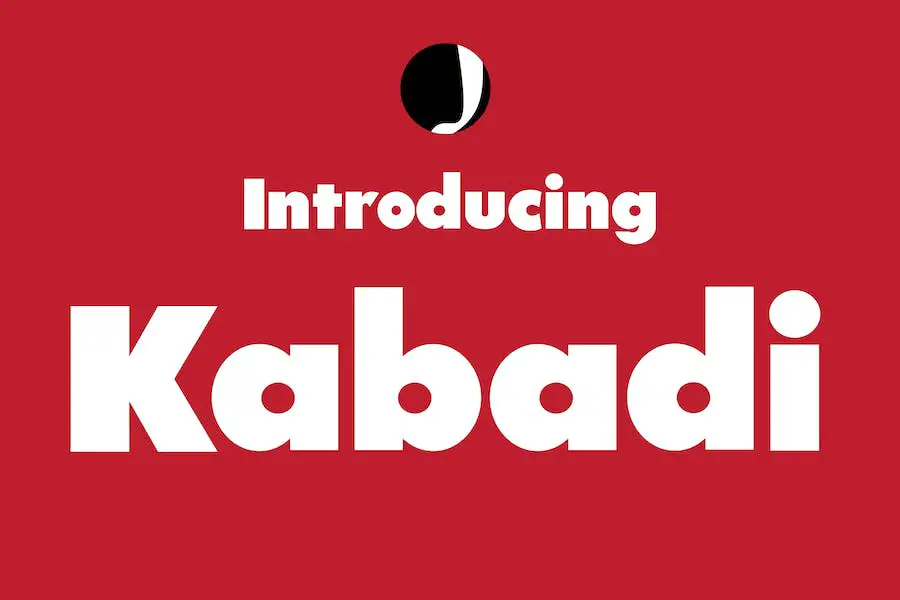
Kabadi es una fuente de visualización en negrita perfecta para diseñadores gráficos que buscan agregar un toque de singularidad a sus proyectos. Con su nombre derivado de la palabra punjabi que significa lucha libre, esta fuente rinde homenaje a la naturaleza vibrante y enérgica del deporte.
Ideal para titulares, diseños de revistas y portadas, Kabadi aporta un elemento poderoso e impactante a cualquier diseño. Sus letras atrevidas y llamativas hacen una declaración y captan la atención de los espectadores.
Ya sea que estés trabajando en un cartel para un evento de lucha libre o diseñando productos para un fanático de la lucha libre, Kabadi agregará ese toque extra a tus creaciones. Sus personajes fuertes y distintivos crean una sensación de emoción e intensidad.
La naturaleza versátil de Kabadi significa que se puede utilizar para varios proyectos, lo que le brinda la flexibilidad de crear diseños impresionantes en diferentes medios. Ya sea que estés usando Canva o Cricut, esta fuente mejorará la apariencia de tu trabajo, haciéndolo destacar entre la multitud.
luchador
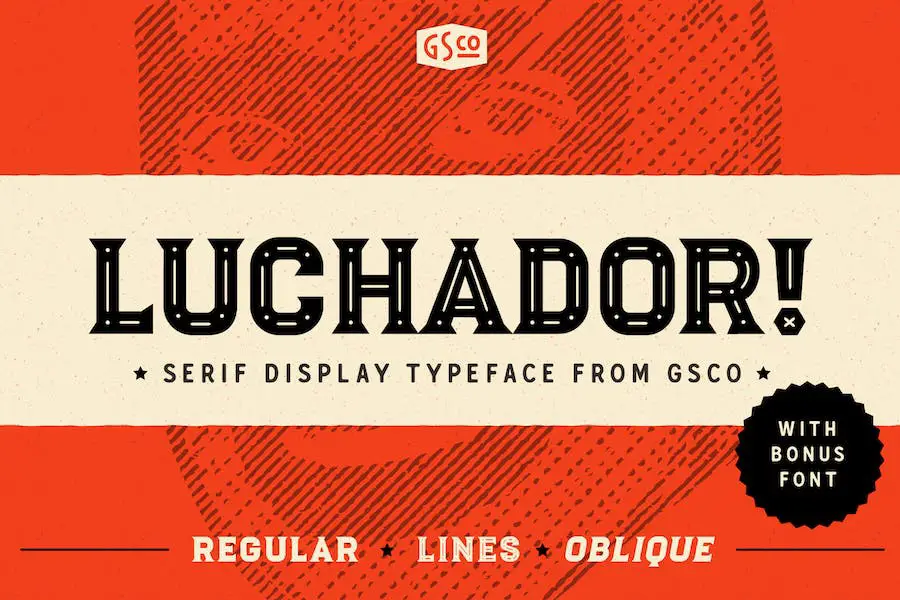
Luchador es un poderoso tipo de letra serif que viene en dos estilos. Con sus adornos en capas, agrega peso, carácter y carisma a cualquier proyecto, como un luchador mexicano.
Ya sea que estés diseñando para impresión o digital, Luchador es la elección perfecta para los diseñadores gráficos que desean llevar sus proyectos al siguiente nivel.
Esta fuente única es perfecta para crear diseños llamativos que se destacan en plataformas de redes sociales como Instagram. Si buscas agregar un toque de audacia y emoción a tus proyectos relacionados con la lucha libre, Luchador es imprescindible.
Los adornos en capas de Luchador te dan la libertad de personalizar tus diseños y agregar profundidad y dimensión. Con sus letras fuertes y atrevidas, Luchador hace una declaración y llama la atención al instante. Es el tipo de fuente que hará que tus diseños destaquen de la página.
Tatuajes de estruendo
¿Buscas una fuente que lleve tus proyectos con temas de lucha libre al siguiente nivel? No busques más que Rumble Tatuajes. Este increíble tipo de letra script, también conocido como It Typeface, está diseñado específicamente para agregar un toque atrevido y cautivador a sus diseños.
Con Rumble Tattoos, puedes crear logotipos impactantes que realmente representen el espíritu de la lucha libre. Sus trazos atrevidos y dinámicos le dan a sus logotipos una presencia poderosa, haciéndolos destacar entre la multitud.
Ya sea que estés diseñando para un evento de lucha libre o un equipo deportivo, esta fuente definitivamente dejará una impresión duradera.
No solo se limita a logotipos, Rumble Tattoos también es perfecto para diseños de carteles. Sus formas de letras únicas y sus detalles intrincados añaden una sensación de dramatismo e intensidad a cualquier cartel.
Ya sea que estés promocionando un combate de lucha libre o creando obras de arte para un evento con temática de lucha libre, esta fuente seguramente llamará la atención de tu audiencia.
MAHIRA
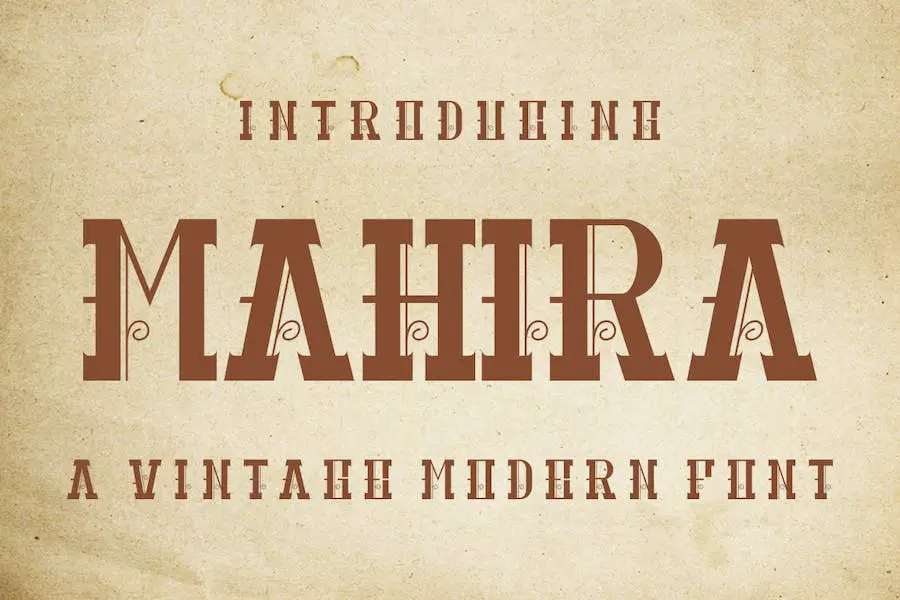
MAHIRA es una fuente de visualización vintage perfecta para diseñadores gráficos que desean mejorar el diseño de sus proyectos. Con sus usos versátiles, esta fuente es una gran adición al conjunto de herramientas de cualquier diseñador.
Con su encanto retro y estilo único, MAHIRA añade un toque de nostalgia a cualquier proyecto de diseño. Sus letras atrevidas y su aspecto icónico ayudan a captar la atención y crear una impresión memorable.
Ya sea que estés trabajando en un logotipo para una cafetería de inspiración vintage o diseñando un cartel para un evento con temática retro, esta fuente agregará el toque perfecto de estilo vintage.
Una de las características más destacadas de MAHIRA es su versatilidad. Se puede utilizar para una amplia gama de proyectos de diseño, lo que la convierte en la fuente preferida de muchos diseñadores gráficos.
La flexibilidad de la fuente permite una integración perfecta en varios estilos y temas de diseño, lo que garantiza que sus proyectos se destaquen entre la multitud.
Merauq
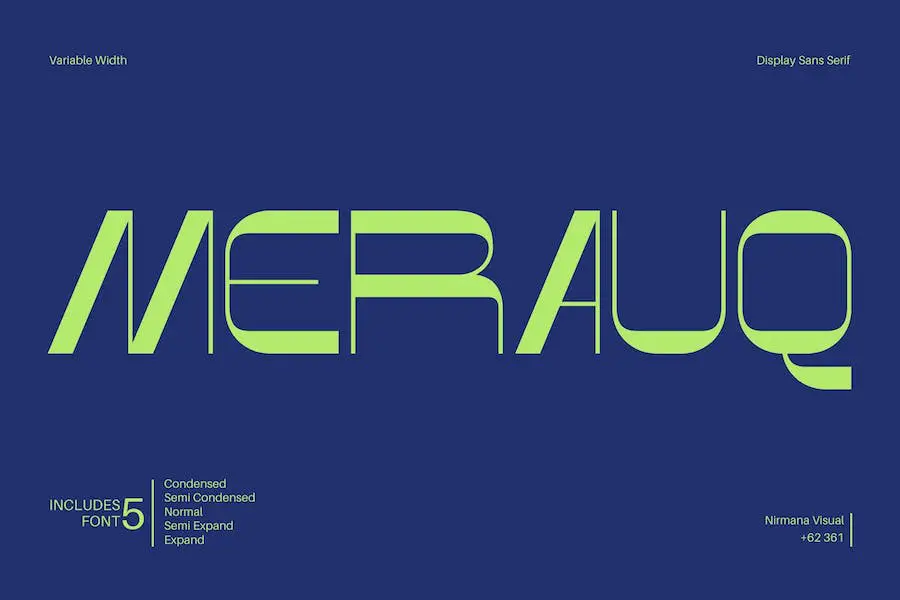
Merauq es una fuente que proporciona una hermosa armonía tipográfica para diversos proyectos de diseño. Con sus 5 anchos, es perfecto para crear logotipos y materiales de marca, publicaciones en redes sociales, anuncios y diseños de productos.
Esta fuente es una herramienta versátil que los diseñadores gráficos pueden utilizar para mejorar el atractivo visual de sus proyectos. Sus 5 anchos permiten flexibilidad y personalización, asegurando que pueda adaptarse a las necesidades específicas de diferentes elementos de diseño.
Ya sea que esté trabajando en el logotipo de una empresa o creando publicaciones llamativas en las redes sociales, Merauq lo tiene cubierto. Su aspecto elegante y armonioso añade un toque de profesionalismo y sofisticación a cualquier diseño.
Los atributos de la fuente la convierten en una excelente opción para los diseñadores que desean mejorar la estética general de sus proyectos. Desde su apariencia limpia y moderna hasta su amplia gama de anchos, esta fuente ofrece infinitas posibilidades para crear diseños visualmente impresionantes.
Cista Simoly
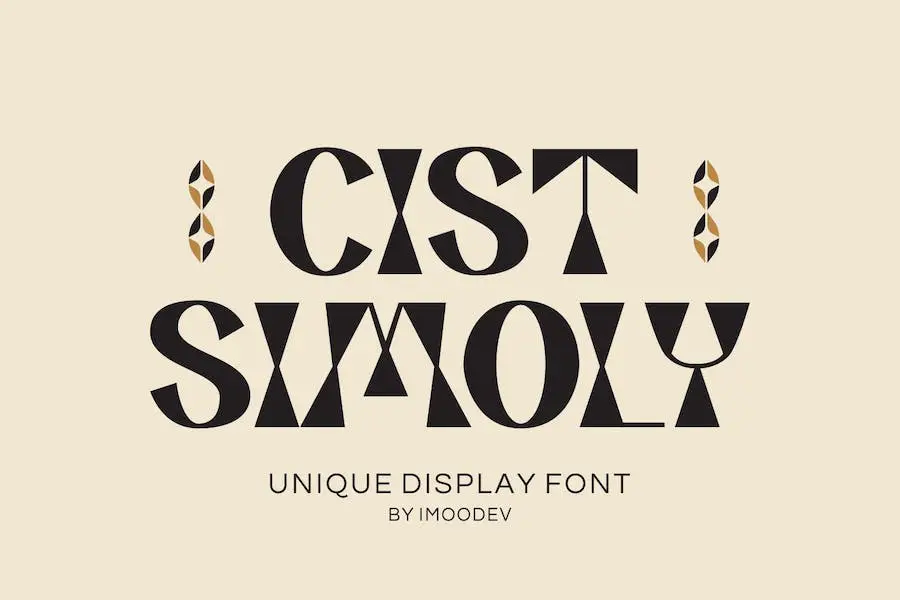
Cist Simoly es una fuente clásica moderna que irradia elegancia visual con sus suaves curvas y hermosas ligaduras. Esta fuente añade un toque de sofisticación a cualquier diseño, haciendo que tu trabajo luzca real y atractivo.
Ya sea que estés creando un logotipo, un póster o un sitio web, Cist Simoly es la fuente perfecta para mejorar el diseño general.
Con su estilo claro y legible, Cist Simoly garantiza que su texto sea fácilmente legible, incluso en tamaños pequeños. Las suaves curvas de las letras le dan a esta fuente un aspecto contemporáneo y elegante, mientras que las ligaduras añaden un nivel extra de refinamiento.
Esta fuente realmente se destaca entre la multitud, permitiéndote hacer una declaración con tu diseño.
Lo que distingue a Cist Simoly es su capacidad para combinar a la perfección elementos clásicos y modernos. Combina el atractivo atemporal de una fuente clásica con las líneas limpias y la sensación contemporánea de una fuente moderna.
Esta combinación única le da a su diseño una sensación de equilibrio y armonía, haciéndolo visualmente atractivo y agradable a la vista.
aturdimiento
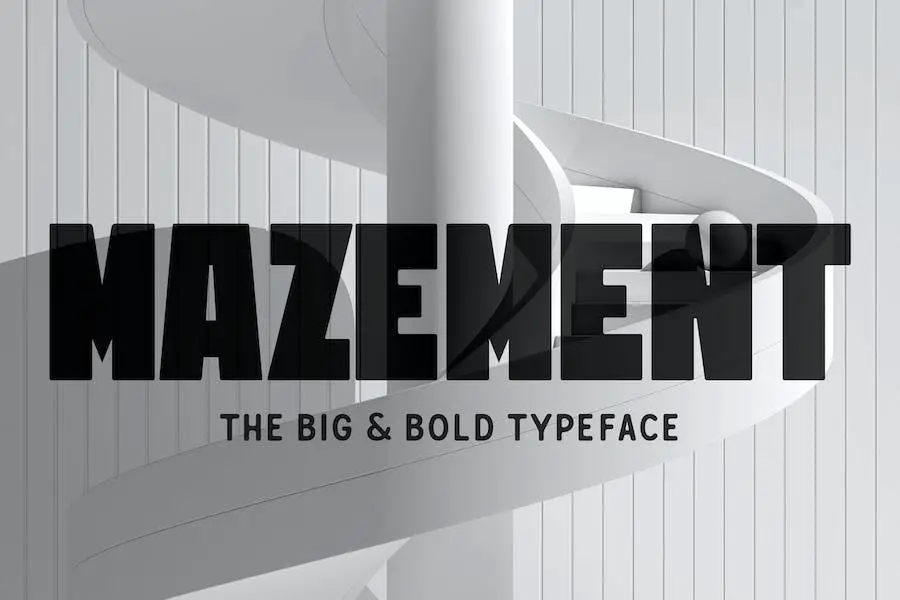
Mazement es un tipo de letra poderoso e impactante que ofrece más de 300 glifos y admite múltiples idiomas latinos. Con su diseño atrevido y macizo, pretende llamar la atención y dominar el espacio que ocupa. Perfecta para visualización y titulares, esta fuente sigue el lema "Cuanto más grande, mejor".
Con Mazement, tendrás acceso a una amplia gama de personajes y símbolos, lo que te permitirá crear diseños llamativos que se destacan. Su gran peso y sus líneas atrevidas lo hacen ideal para llamar la atención y llamar la atención.
Ya sea que esté trabajando en un póster, un logotipo o cualquier otro proyecto de diseño que requiera una fuente llamativa y llamativa, Mazement lo tiene cubierto. Su apariencia espectacular garantiza que su mensaje se transmita alto y claro.
Darkville
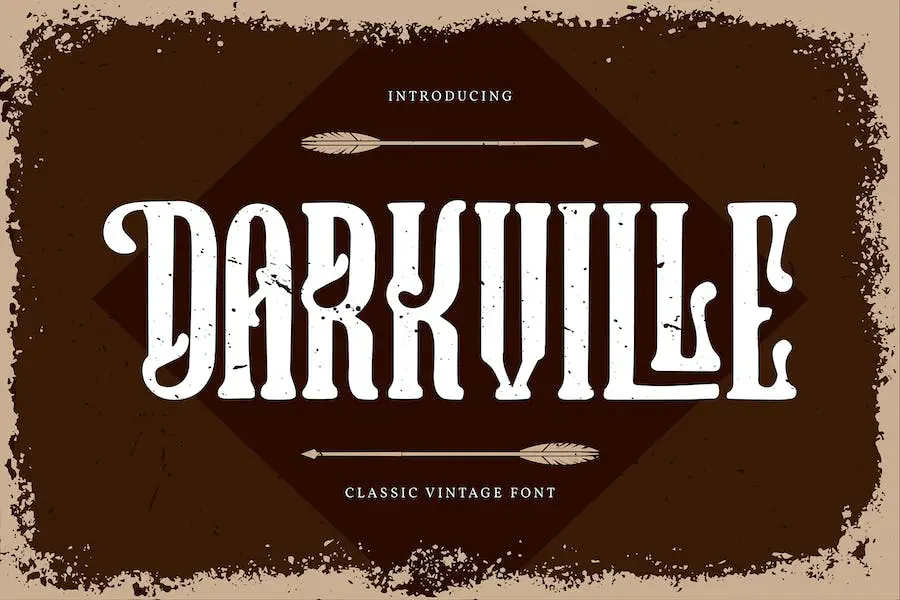
Darkville es una fuente clásica vintage con estilo caligráfico. Agrega un toque de belleza y elegancia a diversos proyectos de diseño, como tarjetas de invitación, tarjetas de felicitación, materiales de marca, tarjetas de presentación, citas y carteles.
Con su aspecto único y atemporal, Darkville es perfecto para añadir un toque vintage y nostálgico a tus diseños. Ya sea que estés trabajando en un proyecto para una boda, un evento especial o simplemente quieras darle a tus diseños un toque clásico, Darkville es una fuente imprescindible para los diseñadores gráficos.
Su versatilidad y atractivo artístico lo convierten en una excelente opción para cualquier proyecto de diseño. Dale a tus diseños un toque de elegancia con Darkville.
Goldrick
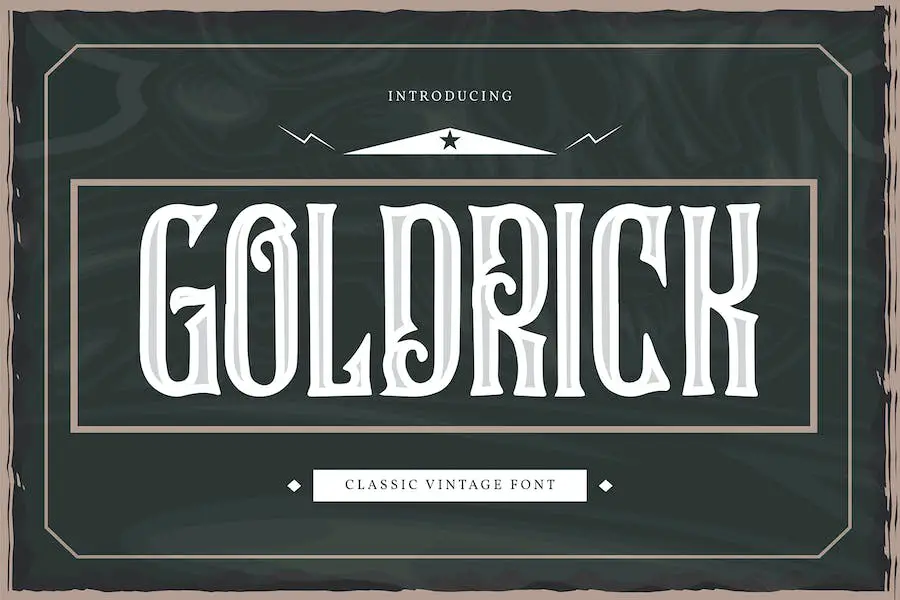
Goldrick es una fuente clásica vintage que cuenta con un hermoso estilo de caligrafía. Es perfecto para mejorar el diseño de diversos proyectos como invitaciones, tarjetas de felicitación, materiales de marca, tarjetas de presentación, citas, carteles y más.
Con su aspecto elegante y con estilo, Goldrick añade un toque de sofisticación a cualquier diseño. Su estilo de caligrafía brinda una sensación clásica y atemporal, lo que la convierte en una fuente ideal para los diseñadores gráficos que buscan mejorar sus proyectos.
Ya sea que esté creando invitaciones de boda o materiales promocionales, Goldrick seguramente impresionará con su estética ornamentada y cautivadora.
Samuel Wickley
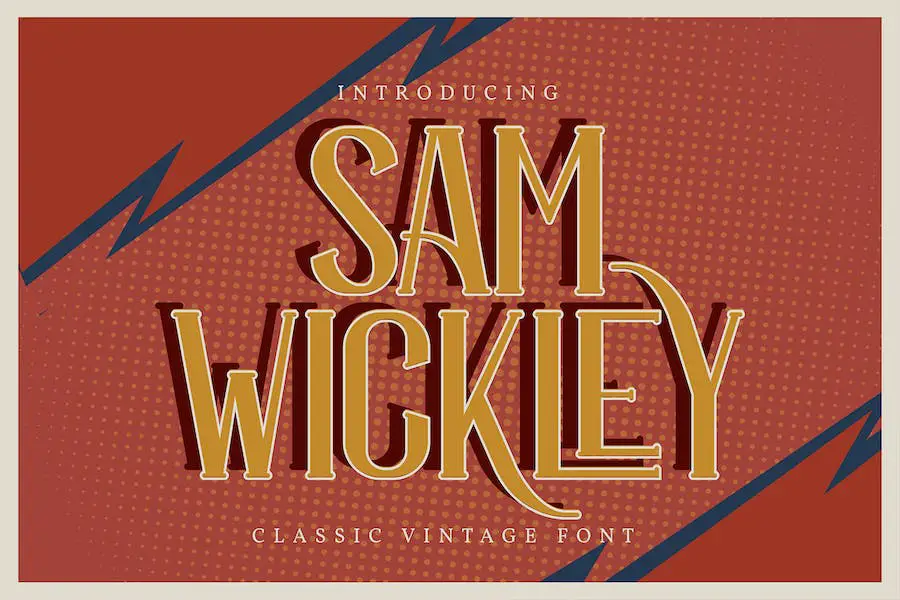
Sam Wickley es una fuente clásica vintage que añade un toque de elegancia y encanto a cualquier proyecto de diseño. Con su estilo de caligrafía, esta fuente es perfecta para crear impresionantes invitaciones, tarjetas de felicitación, materiales de marca, tarjetas de presentación, citas, carteles y más.
Las exquisitas curvas y los intrincados detalles de Sam Wickley lo convierten en una opción destacada para los diseñadores gráficos que buscan mejorar sus proyectos.
Ya sea que esté trabajando en una invitación de boda o en un póster promocional, esta fuente mejorará sin esfuerzo el diseño general y creará una impresión duradera.
Una de las características más destacadas de Sam Wickley es su atractivo atemporal. Con su estética vintage, aporta una sensación de nostalgia y sofisticación a cualquier obra. Capta sin esfuerzo la esencia del diseño clásico y al mismo tiempo mantiene un toque contemporáneo.
Las mejores fuentes de lucha libre gratuitas
¿Buscas agregar una tipografía feroz e impactante a tu próximo proyecto de diseño? ¡No busque más! En esta sección, hemos seleccionado las mejores fuentes de lucha libre gratuitas que seguramente elevarán tus diseños a un nivel de campeonato.
Así que ponte las botas y sumérgete en esta colección: ¡no querrás perderte estas fuentes impresionantes!
Lucha grecorromana lubricada
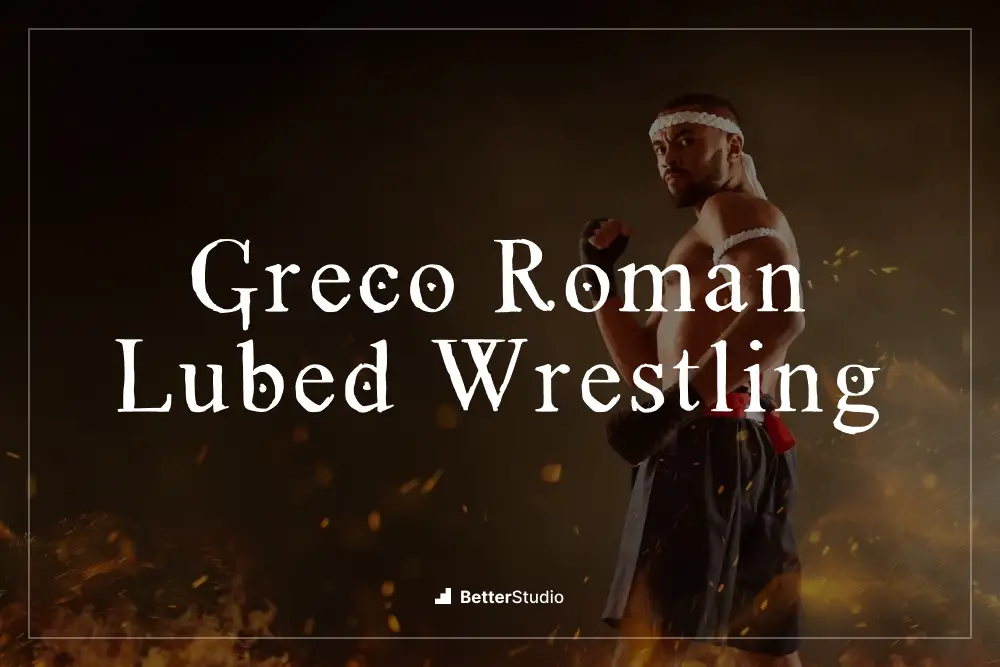
Greco Roman Lubed Wrestling es una fuente diseñada específicamente para diseñadores gráficos que buscan elevar el diseño de sus proyectos. Con su estilo único y líneas elegantes, añade un toque de sofisticación a cualquier diseño.
Esta fuente es perfecta para crear títulos, logotipos o cualquier otro elemento creativo cautivadores que requiera un impacto visual poderoso y dinámico.
Greco Roman Lubed Wrestling combina la elegancia de la tipografía romana tradicional con un toque moderno. Su aspecto elegante y atrevido lo hace ideal para diseños relacionados con los deportes, especialmente aquellos relacionados con la lucha libre.
La curvatura única de la fuente y sus bordes afilados le dan una sensación fuerte y enérgica, capturando perfectamente el espíritu del deporte y añadiendo una sensación de poder e intensidad a sus diseños.
LOGOTIPO DE TNA
TNA Logo es una fuente fantástica que es perfecta para diseñadores gráficos que buscan mejorar sus proyectos. Esta fuente aporta un aire fuerte y audaz a cualquier diseño, lo que la hace ideal para proyectos con temática de lucha libre. Creado por 24hourfonts, agrega un toque único y poderoso a tu trabajo.
La fuente del logotipo TNA tiene un estilo distintivo que captura la esencia de la lucha libre. Sus bordes afilados y líneas fuertes le dan un aspecto resistente e impactante.
Ya sea que estés creando materiales promocionales para un evento de lucha libre o diseñando productos para un fanático de la lucha libre, esta fuente definitivamente hará una declaración.
Una de las características destacadas de TNA Logo es su versatilidad. Funciona bien con varios elementos de diseño, incluidos carteles, logotipos, camisetas y más. Su diseño atrevido y llamativo capta la atención del espectador y deja una impresión duradera.
Con esta fuente, tus proyectos tendrán ese aspecto profesional y pulido que los hará destacar entre la multitud.
Evolucionado
Evolved, creada por JK Typeface, es una fuente fantástica que es perfecta para diseñadores gráficos que buscan mejorar los diseños de sus proyectos.
Esta fuente cuenta con un estilo único y moderno que seguramente llamará la atención. Tiene una apariencia elegante y profesional que puede agregar un toque de elegancia a cualquier diseño.
Evolved viene con una amplia gama de opciones, incluidos diferentes pesos y estilos, lo que permite a los diseñadores elegir la opción perfecta para su proyecto. Ya sea que estés buscando una fuente atrevida y que llame la atención o una más sutil y sofisticada, Evolved tiene lo que necesitas.
Una de las características más destacadas de Evolved es su versatilidad. Se puede utilizar en varios diseños, desde carteles y logotipos hasta sitios web y gráficos de redes sociales. Cualquiera que sea su proyecto, esta fuente puede mejorar su apariencia general.
Pelearse
Brawl, de Baja La Luna Producciones, es una fuente que todo diseñador gráfico debería considerar agregar a su colección. Con su diseño atrevido y poderoso, Brawl es perfecto para crear diseños llamativos e impactantes para cualquier proyecto con temática de lucha libre.
Uno de los atributos destacados de Brawl es su versatilidad. Ya sea que estés diseñando un cartel, un logotipo o un producto para un evento de lucha libre, esta fuente puede aportar ese toque e intensidad extra a tu trabajo.
Grita acción y emoción, lo que lo convierte en la opción ideal para capturar la esencia del mundo de la lucha libre.
Las líneas fuertes y nítidas de la fuente le dan una sensación moderna y atrevida, agregando un toque contemporáneo a sus diseños. Su naturaleza audaz garantiza que su texto se destaque y sea fácilmente legible, incluso desde la distancia. Brawl llama la atención y exige ser notado.
Caída retumbante
Rumble Tumble, creada por Iconian Fonts, es una fuente perfecta para diseñadores gráficos que buscan mejorar el diseño de sus proyectos. Con su estilo único y llamativo, esta fuente seguramente hará que tus diseños se destaquen.
Uno de los atributos destacados de Rumble Tumble es su versatilidad. Ya sea que esté trabajando en un póster, un logotipo o incluso un sitio web, esta fuente se puede utilizar de diversas formas para mejorar su diseño. Su aspecto atrevido y vanguardista añade un toque de emoción y energía a cualquier proyecto.
Otra gran característica de Rumble Tumble es su legibilidad. Incluso con su diseño atrevido y único, las letras siguen siendo fáciles de leer, lo que las convierte en una opción práctica tanto para los títulos como para el cuerpo del texto. No es necesario sacrificar la claridad por el estilo con esta fuente.
Preguntas frecuentes
Las fuentes de lucha libre son tipos de letra únicos que se inspiran en la estética atrevida y dinámica de la lucha libre profesional. Estas fuentes suelen presentar bordes nítidos, letras en negrita y una sensación de energía y poder que captura la esencia del deporte.
Las fuentes de lucha libre han ganado popularidad debido a su capacidad para agregar un elemento visual fuerte e impactante a varios proyectos relacionados con la lucha libre.
Ya sea que estés creando materiales promocionales, diseñando un sitio web de lucha libre o incluso haciendo fan art, estas fuentes pueden ayudarte a transmitir la emoción y la intensidad asociadas con el deporte.
Las fuentes de lucha libre se pueden utilizar de diversas formas. Se utilizan comúnmente para diseñar carteles de lucha libre, pancartas de eventos, camisetas, logotipos y otros productos.
Además, las fuentes de lucha libre también se pueden utilizar en proyectos digitales, como gráficos de redes sociales, miniaturas de YouTube y encabezados de sitios web, para darles un aspecto audaz y distintivo.
Conclusión
Para resumir, hemos explorado las 15 mejores fuentes de lucha libre en este artículo. Hemos analizado cómo estas fuentes pueden mejorar el diseño de sus proyectos y aportar una sensación de emoción y energía.
Ya sea que esté creando un póster, un sitio web o cualquier otro proyecto de diseño gráfico con temática de lucha libre, estas fuentes seguramente causarán una declaración.